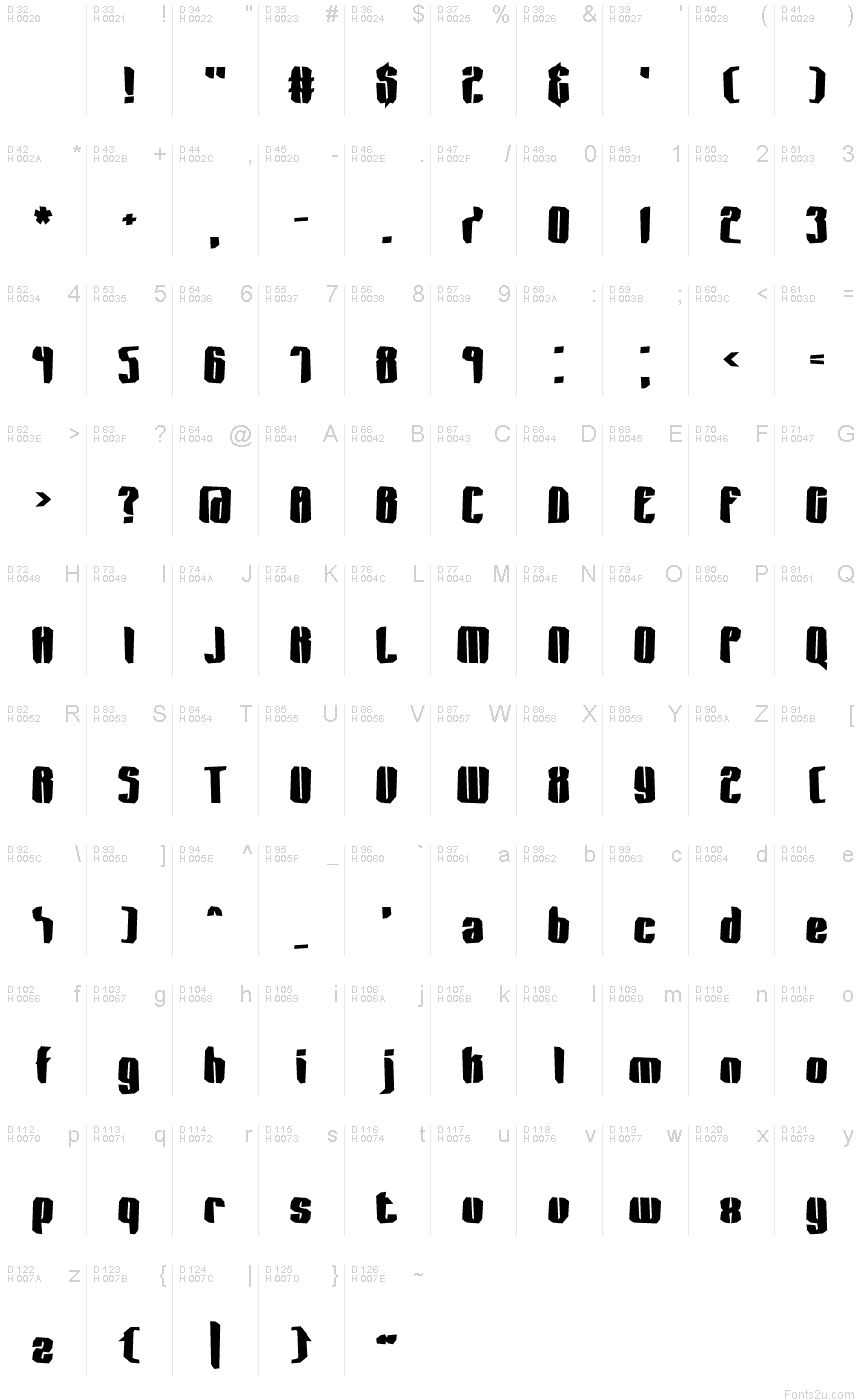
Wager Lost BRK
Wager Lost od AEnigma Fonts to darmowy, zniekształcony krój pisma typu display w stylu gotyckim, o surowym charakterze przypominającym wycinanki z papieru. Litery opierają się na masywnych pionowych liniach i przyciętych rogach, przełamując tę klasyczną surowość nieregularnymi kątami i lekko poszarpanym rytmem, co nadaje krojowi surowy, głośny i nieco niepokorny wyraz.
Dzięki temu ten darmowy font naturalnie sprawdza się na plakatach, okładkach płyt, zinach, w identyfikacji wizualnej lokali czy w tytułach gier, gdzie potrzebujesz średniowiecznego klimatu bez ceremonialnej sztywności. Świetnie nadaje się również do krótkich nagłówków i logotypów, ponieważ gęste kształty i ostre cięcia sprawiają, że nawet kilka liter ma odpowiednią wagę.